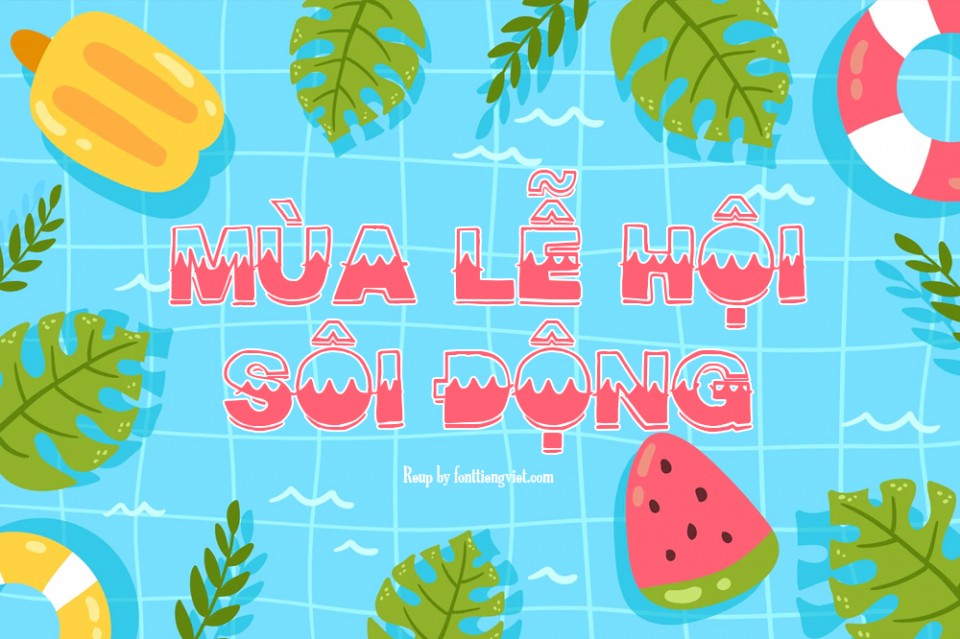
Font việt hóa LNTH Midsummer Circus
Font việt hóa LNTH Midsummer Circus mang phong cách cổ điển độc đáo
Font việt hóa LNTH Midsummer Circus là một bộ phông chữ mang đậm phong cách vintage và nghệ thuật rạp xiếc cổ điển. Khi bạn tìm kiếm một Font Miễn Phí để làm nổi bật các thiết kế mang hơi hướng hoài cổ, đây chính là lựa chọn không thể bỏ qua. Với các đường nét trang trí tỉ mỉ và cấu trúc chữ vững chãi, bộ phông này giúp tái hiện không gian rực rỡ của những buổi diễn giữa mùa hè, tạo nên một sức hút thị giác mạnh mẽ cho mọi dự án đồ họa hiện nay.
Khám phá vẻ đẹp của Font việt hóa LNTH Midsummer Circus
Bộ chữ này nổi bật với các chi tiết cách điệu tinh xảo, gợi nhớ đến những tấm bảng hiệu quảng cáo từ thế kỷ trước. Việc sử dụng Font việt hóa LNTH Midsummer Circus giúp các nhà thiết kế giải quyết triệt để vấn đề lỗi font khi gõ tiếng Việt, đảm bảo sự đồng nhất và chuyên nghiệp. Các dấu câu được đặt vị trí hợp lý, giữ nguyên linh hồn của bản gốc nhưng vẫn mang đậm bản sắc ngôn ngữ Việt Nam, phù hợp cho nhiều mục đích khác nhau.
Ứng dụng trong giáo dục và trang trí sự kiện
Trong môi trường học đường, phông chữ này thường được các bạn học sinh và giáo viên ưa chuộng để thiết kế thiệp mời sự kiện, trang trí báo tường hoặc làm tiêu đề cho các bài thuyết trình chủ đề văn hóa. Sự độc đáo của nó giúp khơi gợi trí tưởng tượng và làm cho các nội dung giáo dục trở nên sinh động, bắt mắt hơn, đồng thời giúp các thông điệp quan trọng dễ dàng ghi dấu ấn trong lòng người xem ngay từ cái nhìn đầu tiên.
Lưu ý khi sử dụng Font việt hóa LNTH Midsummer Circus
Để đạt hiệu quả thẩm mỹ tốt nhất, người dùng nên kết hợp bộ phông này với những gam màu nóng như đỏ, vàng hoặc các tông màu pastel để tạo cảm giác cổ điển. Do đặc tính nhiều chi tiết trang trí, bạn nên sử dụng phông chữ này cho các đoạn văn bản ngắn hoặc tiêu đề lớn thay vì các đoạn văn bản dài để tránh gây rối mắt. Sự kết hợp thông minh sẽ giúp tác phẩm của bạn đạt đến độ hoàn thiện cao nhất về mặt thị giác.
Kết luận về bộ phông chữ nghệ thuật